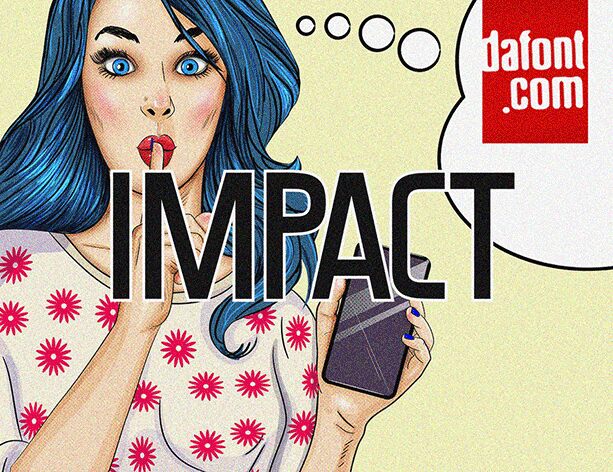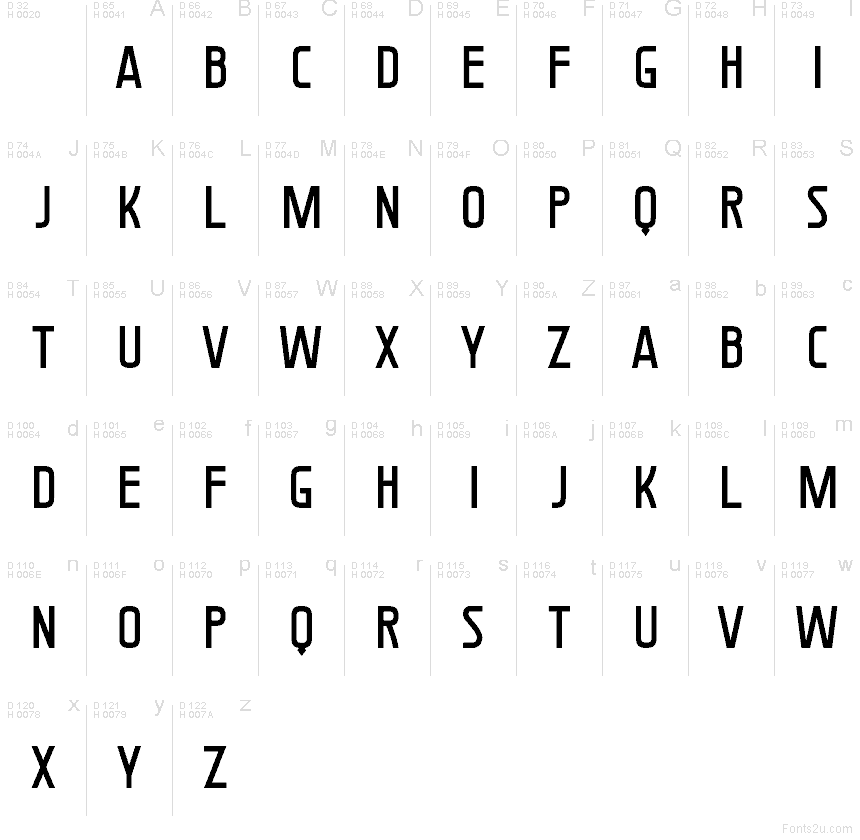
Impact Extravagant Regular
Impact Extravagant von Vladimir Nikolic ist eine kostenlose, schmale serifenlose Schrift mit der direkten, wuchtigen Ausstrahlung von Plakatdesigns. Die Großbuchstaben wirken hoch, reduziert und ausdrucksstark. Ihre schmalen Proportionen und die starke vertikale Dynamik verleihen selbst einfachen Formen einen harten, urbanen Rhythmus.
Sie eignet sich hervorragend für Magazintitel, Musik-Flyer, Sport-Branding, Title Cards und Social-Media-Grafiken mit prägnanten Schlagwörtern, bei denen wenige Buchstaben maximale Wirkung erzielen müssen. Als Freefont ist sie zudem eine starke Wahl für Mastheads, Zitate und kompakte Headline-Systeme, da die gestauchten Versalien viel Kraft auf engem Raum entfalten, ohne überladen zu wirken.